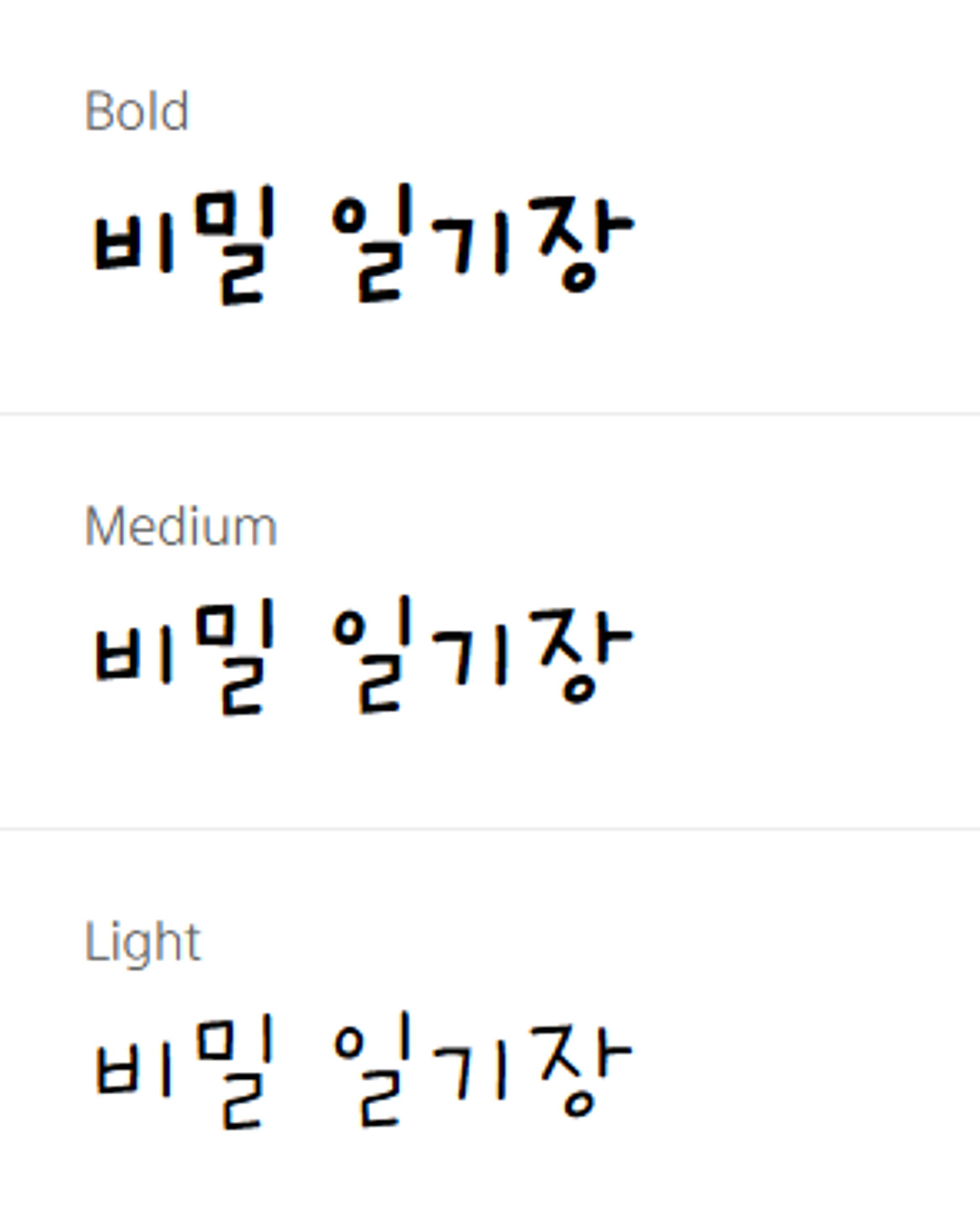
Rix받아쓰기
공부왕찐천재에서 자주 등장하는 폰트입니다. 말자막이 아닌 상황묘사나 정보제공 자막에 나오네요. 어떤 폰트인지 궁금합니다.
이거 카카오프렌즈 이벤트에 있는 서체인데 무슨서체인가요??? 왠지 유료일거같은데 유료서체 이름이랑,,, 이거 비슷한 무료서체도 알려주시면 너무 감사하겠습니다 ㅠㅠ